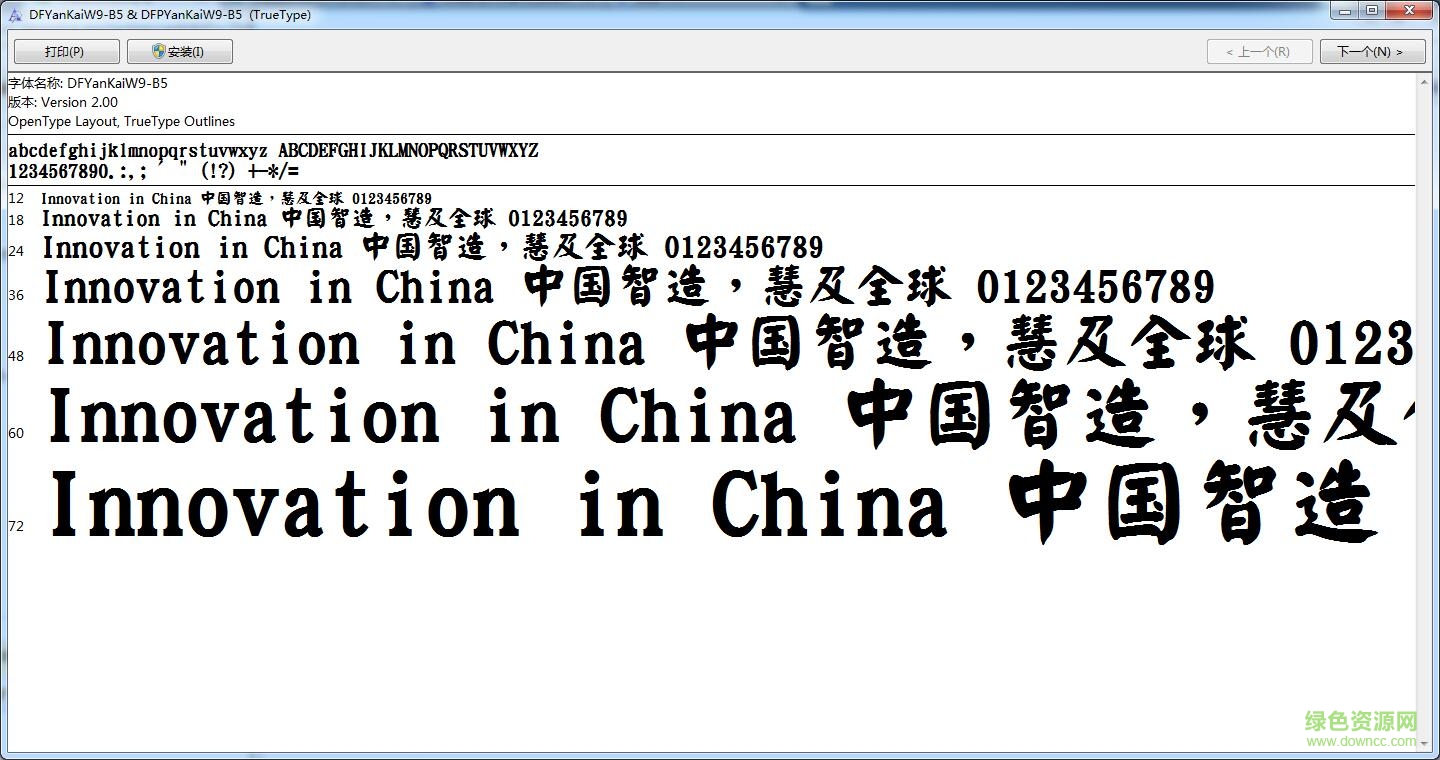
華康正顏楷體w9字體簡單大方。這款字體看起來有些粗條,在進行商標注冊以及公司設計logo方面很受歡迎!字體完全免費,需要的用戶可以來本站下載。
華康正顏楷體w9是一款應用于廣告創(chuàng)意設計方面的簡體中文字體,該字體比較粗壯,字形大方得體,整體效果十分出色,字庫完整,可以適用于名片設計、平面設計、廣告設計、報紙雜志、企業(yè)LOGO、商標注冊、電視臺廣告等領域!歡迎大家來綠色資源網(wǎng)免費下載使用。